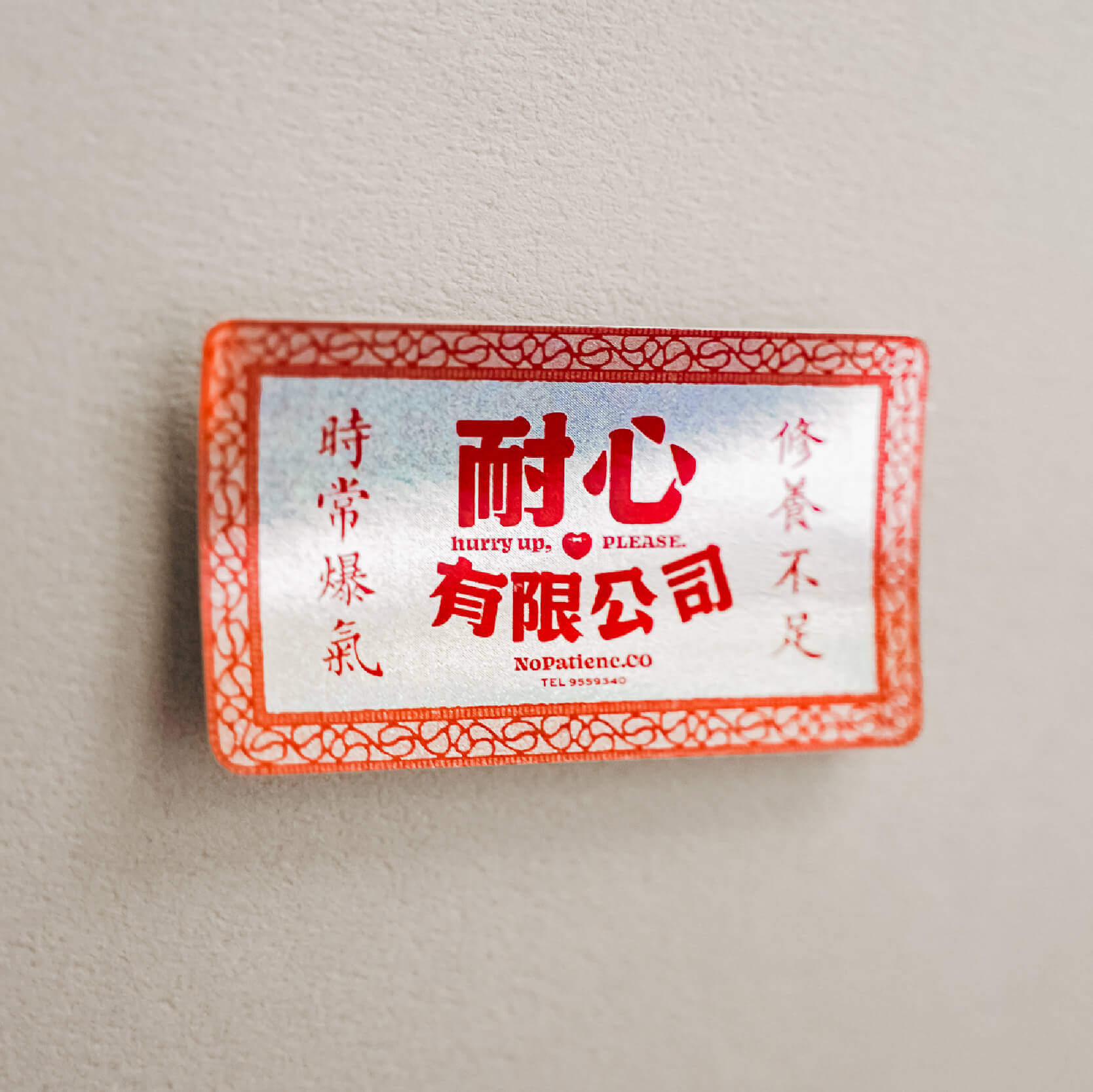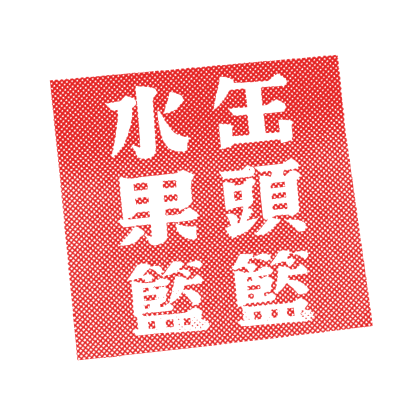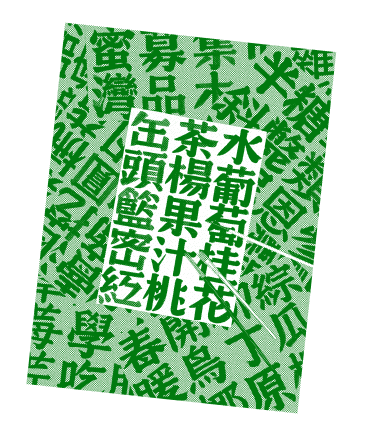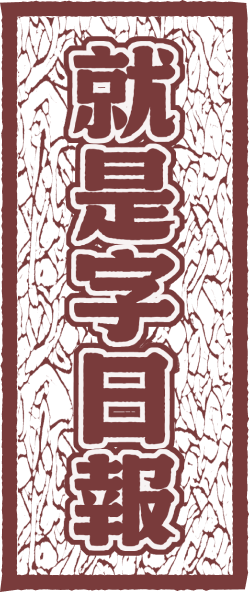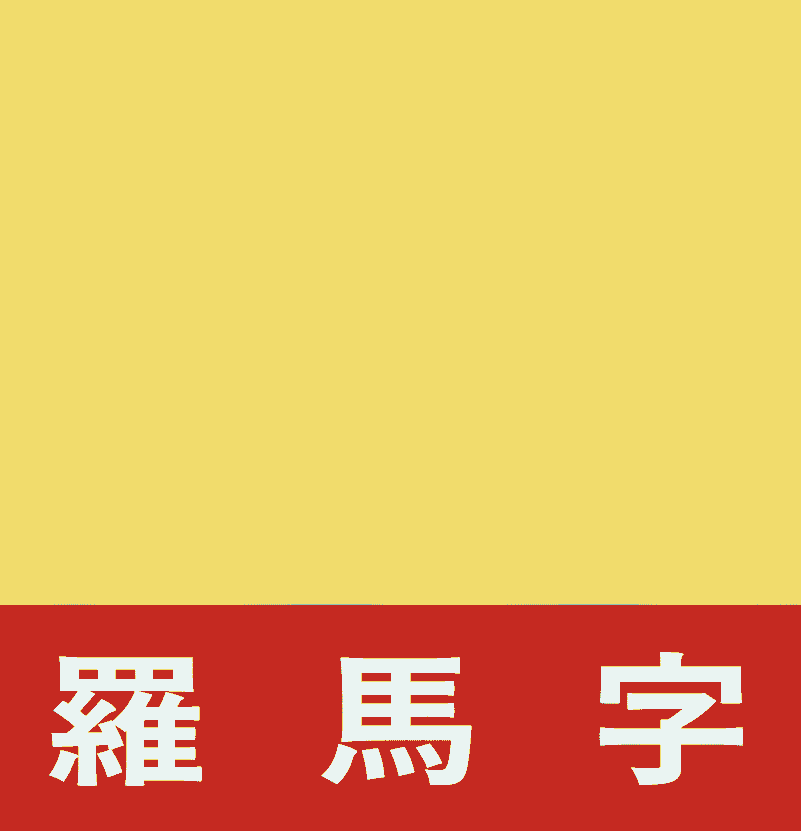
想重現人味
所以從「畫字」開始
設計師采柔為了探究「什麼是生根於台灣土壤的字體?」,到處採集有「人味」的字。老街的招牌看板、舊書標題和廟宇執事牌⋯⋯。
然後采柔便循古法,像招牌師傅一樣提起筆畫字。也正因親手繪製,激盪出不同於數位設計的獨特魅力。
一點點不一樣,讓柑仔蜜帶你穿越時空
回憶裡總有些滋味不想忘記。保留過去手繪字的特色寫法,正是這幾筆不同,讓柑仔蜜一登場就重現時代風景。
字體預計將優先顯示常見寫法,特色寫法註➊以替換字符功能註➋保留於字型檔,可隨設計需求自由選用。
生長在台灣
説什麼語言都會通!
柑仔蜜預計製作超過 8000 字,支援台灣日常編排的需求。配有獨家設計的窄體歐文與數字,混排設計輕鬆不費力。將支援台語、客語常用漢字以及羅馬字、原住民族語註➌以及預購者的姓名罕用字註➍!
要台味復古的 IG 字體? 要風趣可愛的網頁標題?
要大氣典雅招牌設計?來點柑仔蜜,全都能搞定!
以在地風土為核心
,改變台灣的文字風景
柑仔蜜親切趣味,設計過程卻一點也不輕鬆
設計師采柔投注大量時間心血,
掙扎於在地脈絡與數位呈現的兩難
酸甘甜 ê 台灣古早味
就是柑仔蜜
柑仔蜜預計製作超過 8000 字,包含常用漢字、歐文、數字、注音符號等基本字符。另涵蓋台語、客語漢字及羅馬字,還有原住民族語、香港常用漢字,以及預購者的姓名罕用字。